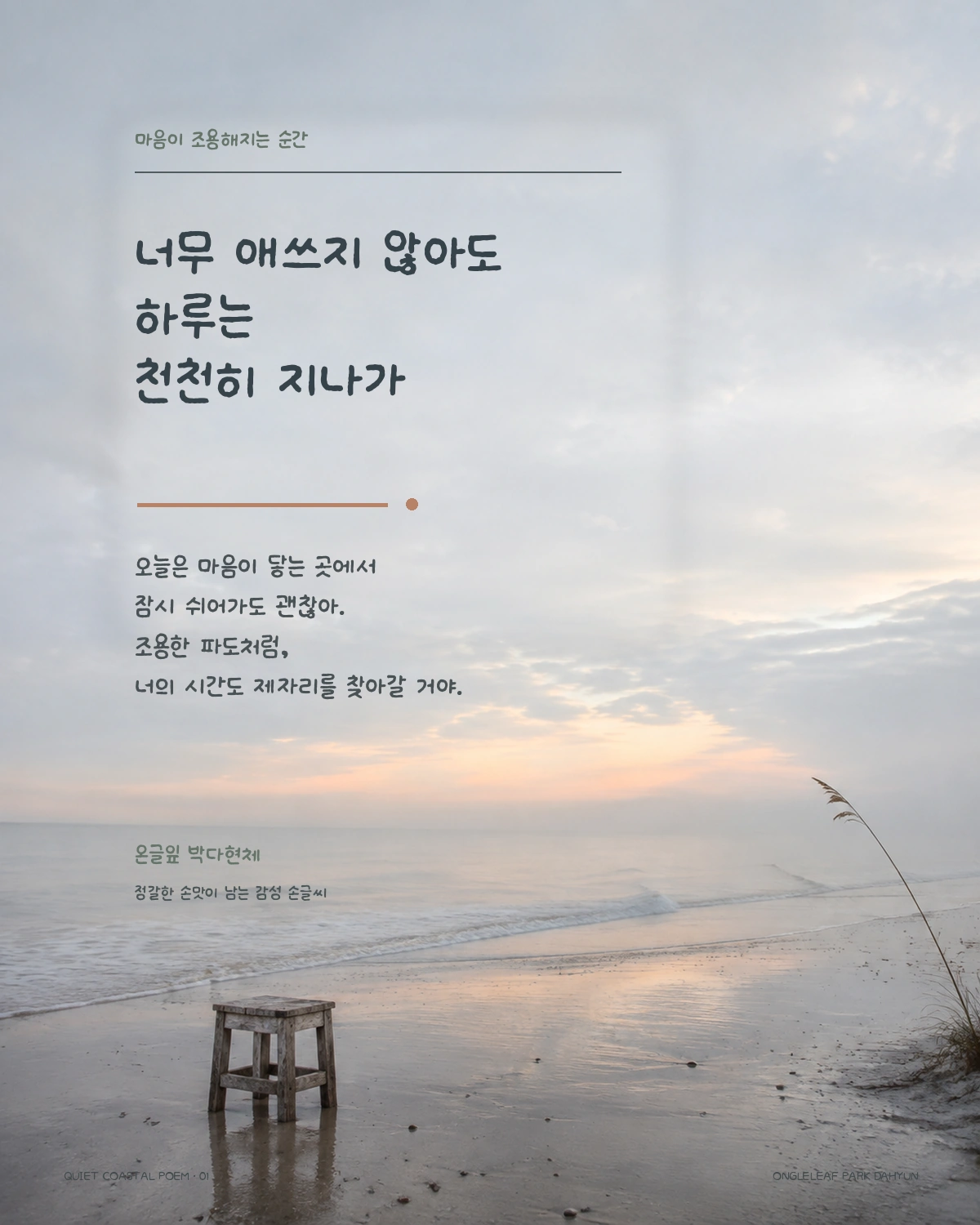
온글잎 박다현체 — 온글잎에서 배포하는 무료 폰트입니다. 정갈하게 눌러쓴 획에 고양이 그림 기호까지 들어 있어, 손맛과 재미를 함께 지닌 손글씨체
온글잎에서 2023년에 나온 손글씨 서체로, 이름 그대로 박다현 님의 글씨입니다. 온글잎 계열 가운데 가장 많이 쓰이는 서체이기도 합니다.
조형 설명은 없지만 디자이너가 남긴 한마디에 힌트가 있습니다. 인사말 뒤에 귀여운 고양이들도 많이 써 달라면서 특수기호 몇 개를 나란히 적어 두었는데, 그 자리에 고양이 그림이 들어 있는 것으로 보입니다. 실제로 이 서체로 고양이를 찍는 방법을 찾는 사람들이 있습니다. 다만 어느 자리에 무엇이 들어갔는지는 제작사가 밝히지 않았으니 직접 눌러 보고 확인하세요.
형태는 파일을 보고 적습니다. 받침이 붙을 때 높이가 달라지는 탈네모틀이고 낱자가 가로로 퍼져 있어 크레파스로 눌러 쓴 듯한 인상을 냅니다. 굵기는 하나이고 한글은 2,780자라 드문 음절은 빠질 수 있습니다. 상업적으로 쓸 수 있고 임베딩과 BI, CI도 되지만 폰트 수정은 금지됩니다.